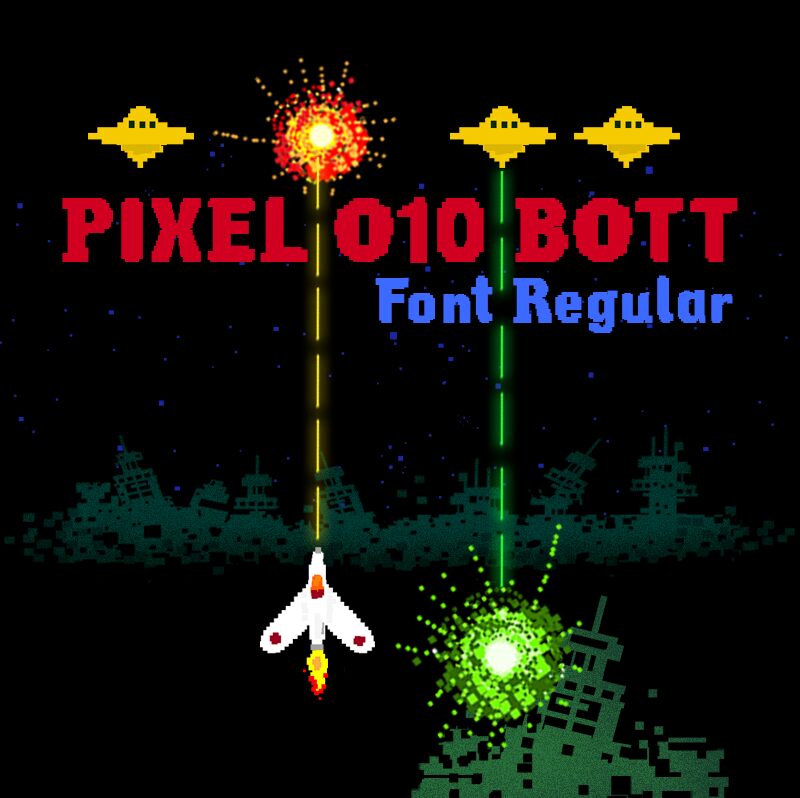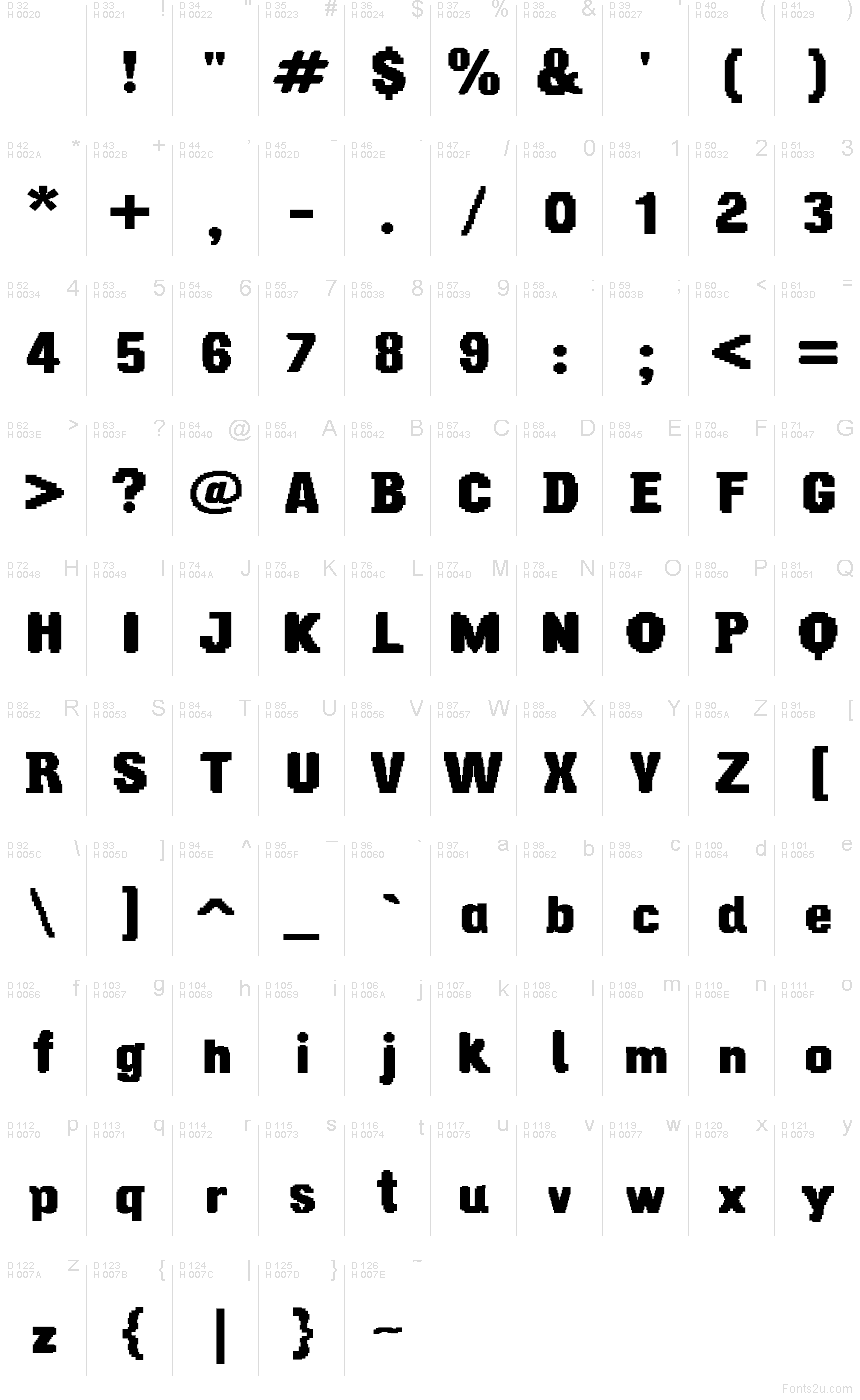
Pixel O10 Bott od Galdino Otten Fonts je bezplatné digitální display písmo s hutnou siluetou v arkádovém stylu. Široká písmena přerušují ostré pravoúhlé zářezy a nestejnoměrné šířky propůjčují tvarům drsnou, strojově řezanou texturu. Tloušťka působí důrazně a kompaktně.
Designéři pracující v oblasti retro her a elektronické hudby jej shledají obzvlášť vhodným pro titulkové karty a reklamní předměty, kde neotesané tvary evokují grafiku starého hardwaru. Plakáty jsou jeho nejsilnějším využitím, neboť nápis připomíná údernost poutače arkádového automatu.